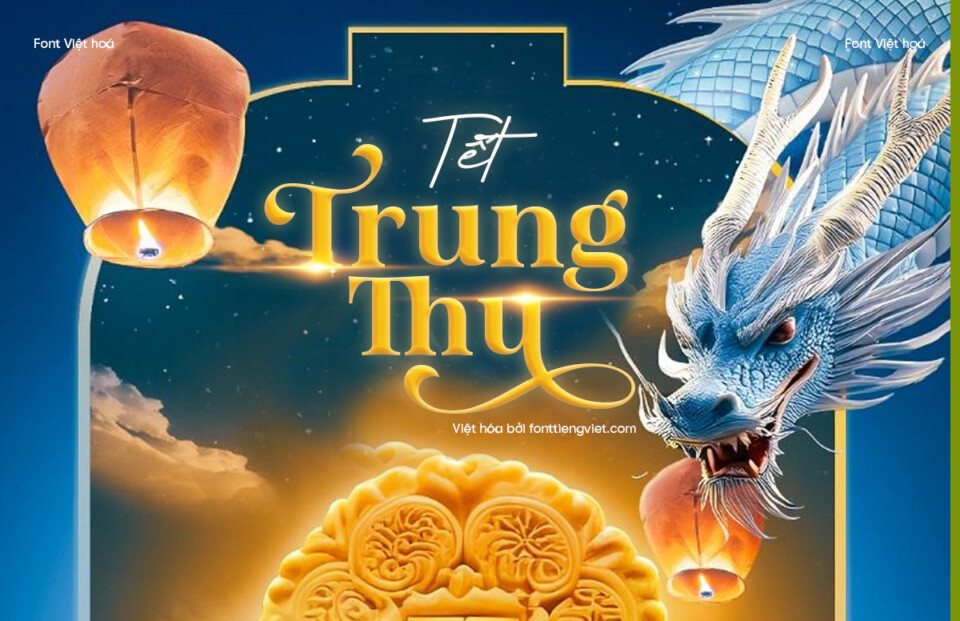
Để tạo ra những chiến dịch truyền thông và ấn phẩm thiết kế ấn tượng cho rằm tháng Tám, việc sở hữu một bộ sưu tập phông chữ đa dạng là điều kiện tiên quyết. Không cần phải mất thời gian tìm kiếm và thử nghiệm từng phông chữ đơn lẻ, Combo 2 – Font Việt hoá Trung thu 2025 mang đến cho bạn một “hệ sinh thái” typography hoàn chỉnh, giúp tối ưu hóa luồng công việc và thăng hoa ý tưởng.
Khám Phá Sức Mạnh Của Combo 2 – Font Trung Thu 2025
Khác với các bộ font lẻ, một combo được tuyển chọn kỹ lưỡng sẽ giải quyết bài toán đa dạng hóa phong cách thiết kế của bạn. Bộ Combo 2 quy tụ những phông chữ xuất sắc nhất dành riêng cho mùa lễ hội năm nay, được việt hóa 100% với chất lượng hiển thị sắc nét nhất.
• Đa dạng phong cách (Versatility): Từ nét chữ thư pháp mềm mại truyền thống, phông chữ Retro hoài cổ, cho đến những đường nét phá cách, hiện đại. Combo này bao trọn mọi concept thiết kế bạn cần.
• Việt hóa đồng bộ: Toàn bộ các font trong gói đều được xử lý kerning (khoảng cách chữ) và tối ưu hóa bộ dấu tiếng Việt cực kỳ tỉ mỉ, cam kết không lỗi phông trên mọi phần mềm thiết kế.
• Dễ dàng kết hợp (Font Pairing): Các phông chữ trong bộ sưu tập được lựa chọn để có thể “mix & match” hoàn hảo với nhau. Bạn có thể dùng một font Display ấn tượng cho Tiêu đề và một font Sans-serif thanh lịch cho nội dung mô tả.
Tại Sao Designer Cần Sở Hữu Combo Này?
Ứng Dụng Đa Chiều Cho Mùa Lễ Hội
Bộ Combo 2 này là nguồn tài nguyên vô giá cho hàng loạt các hạng mục:
• Bao bì & Nhãn mác: Thiết kế hộp bánh Trung Thu, tem nhãn trà, quà tặng doanh nghiệp với đa dạng concept từ cổ điển hoàng gia đến hiện đại, tối giản.
• Truyền thông Social Media: Sáng tạo các bài đăng tương tác, mini-game, banner cover Facebook, Zalo mang đậm không khí rộn rã.
• Thiết kế In ấn & POSM: Backdrop sân khấu đêm hội trăng rằm, standee sự kiện, tờ rơi khuyến mãi dịp Tết Thiếu nhi.